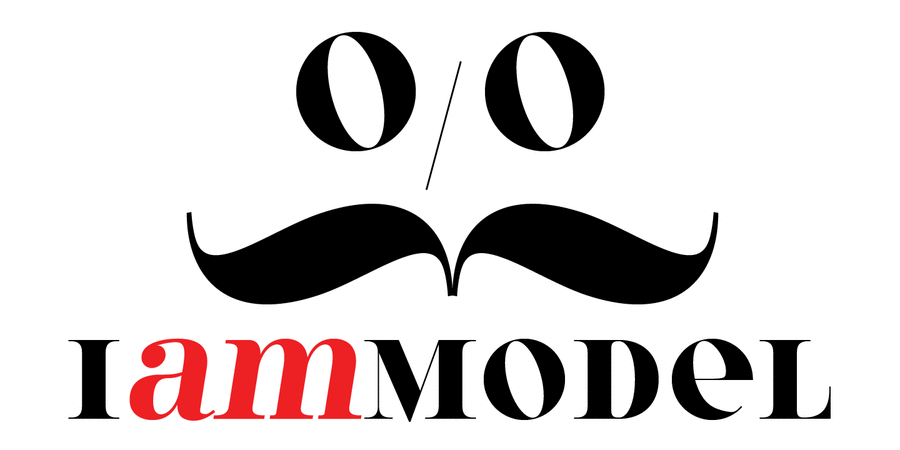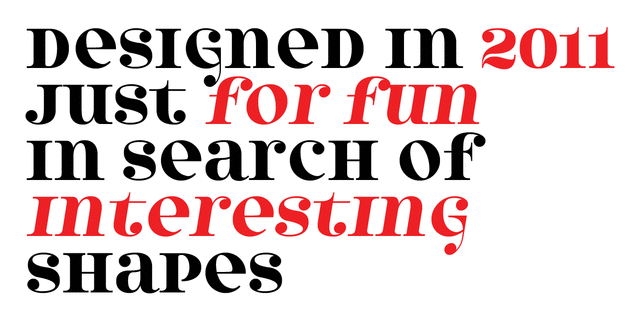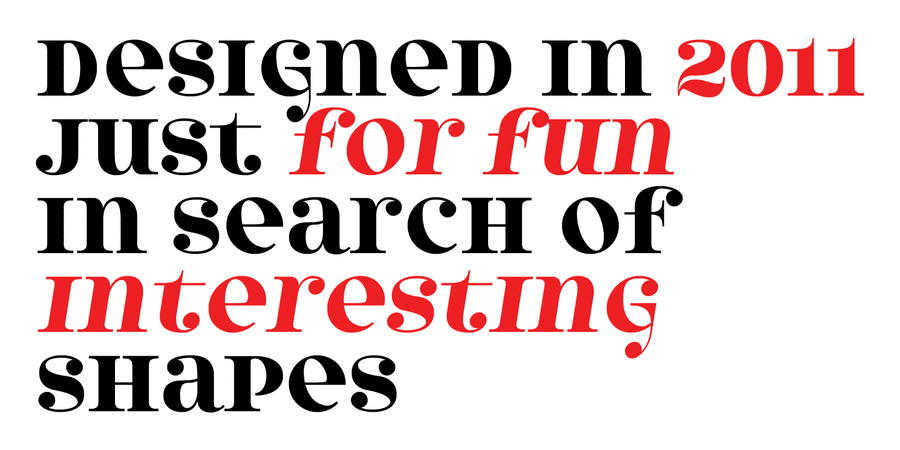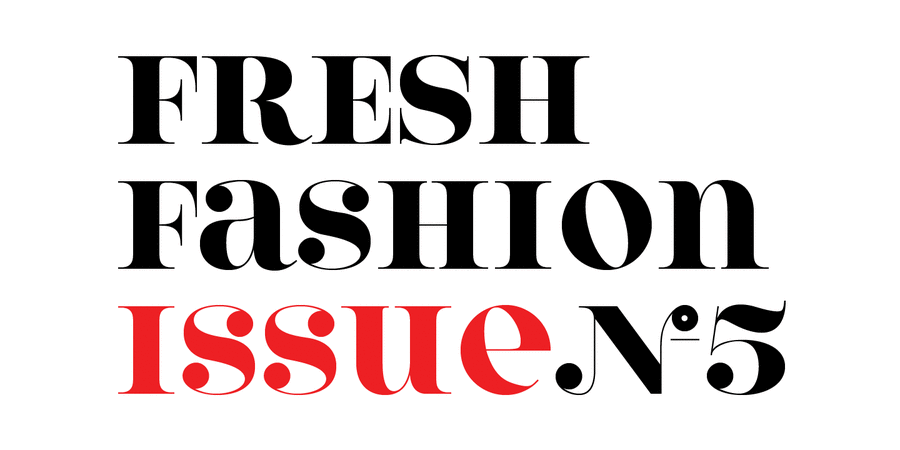
About Model 4F UnicaseШрифт для заголовков, плакатов и журналов. Разработан Сергеем Ткаченко в 2011 году.
Associations for font family Model 4F UnicaseTypeface personality and character:
spectacular, refined, original, fashionable, Glamorous, festive, brilliant, luxurious, rich, sharp, glossy, distinctive, mannered, pretentious, plastic, salon art, sexy, romantic, masterful, beautiful, splashy, attractive, voiced, jewelry, extravagant, esthetic, nonconformist, experimental, proud, theatrical, dramatic, passionate, dynamic, pretty, nice, expensive, select, elite